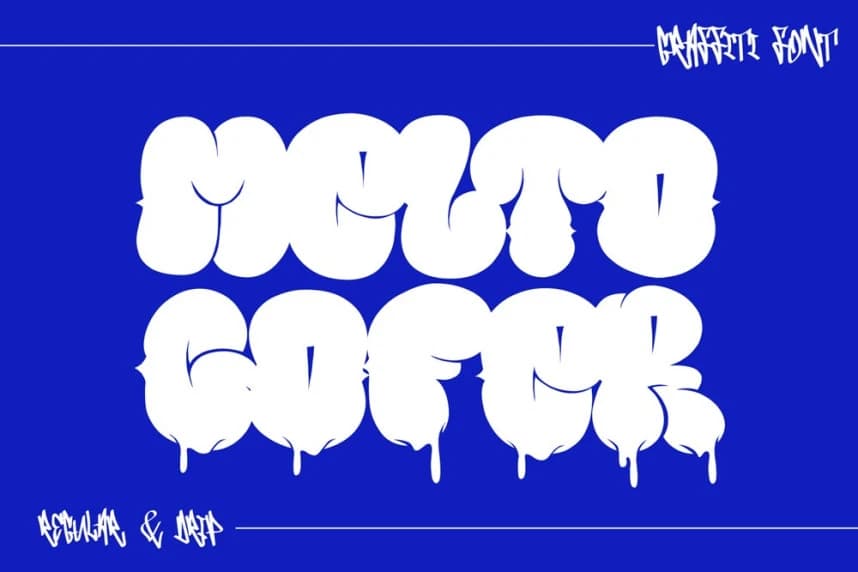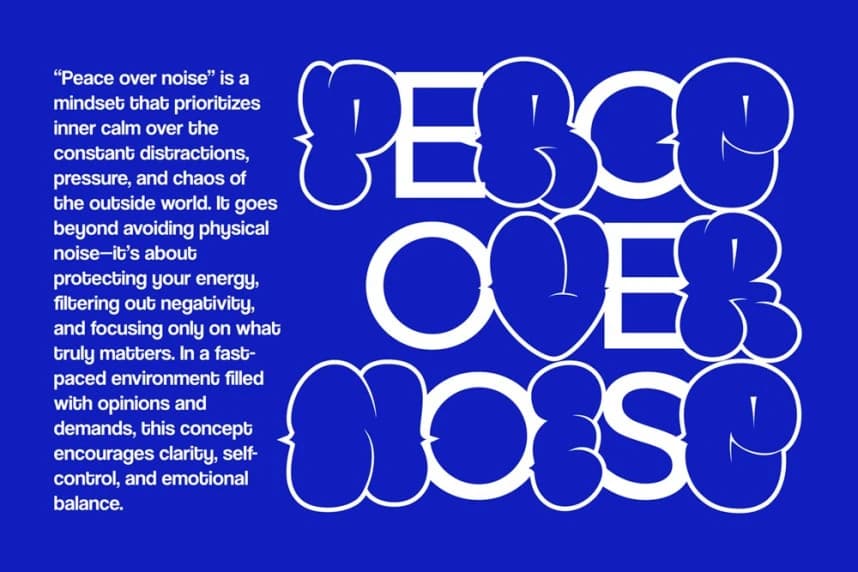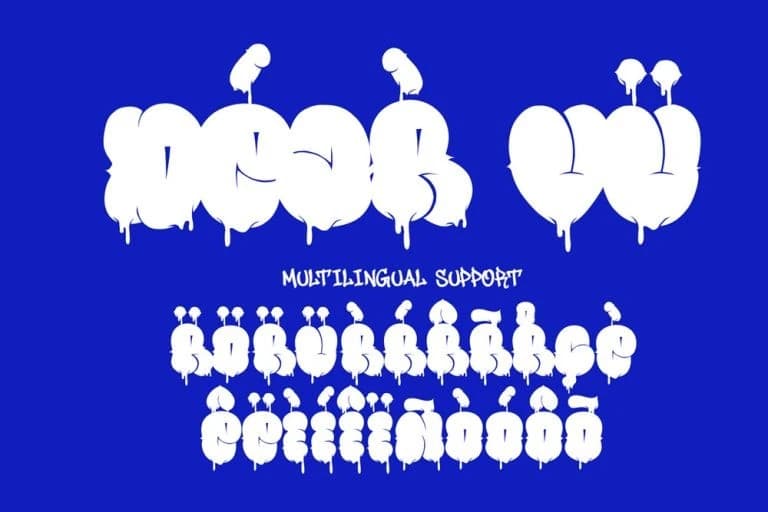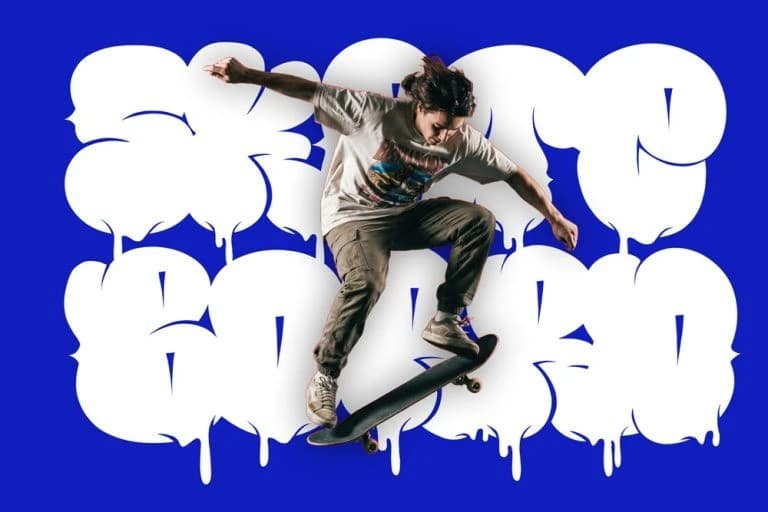
Melto Gofer Font
Melto Gofer Font, klasik throw-up yazı tiplerinden ve balon tarzı sokak sanatından ilham alan cesur ve eğlenceli bir grafiti fontudur. Şehir etiketlemesinin hızlı, ifade dolu enerjisini yakalamak amacıyla tasarlanan bu balon grafiti fontu, yuvarlak hatları damla efektleriyle birleştirerek dinamik bi